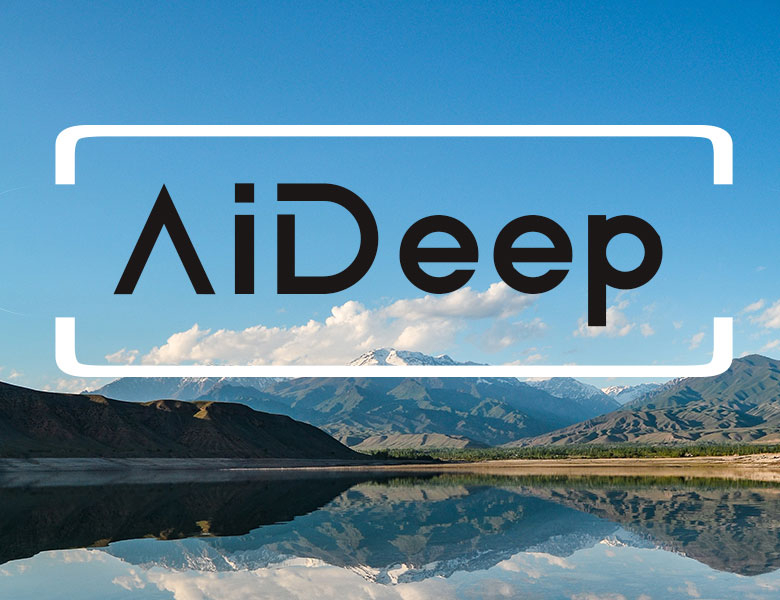
AiDeep字體是由網絡尖刀用戶體驗中心UED團隊出品的一套由公司品牌命名的免費開源字體。中文字體做了700多個,實在做不動了,所以先發了26個英文大寫+26個英文小寫,額外0-9這10個阿拉伯數字。
背景:團隊今年定位國際化,將大部分業務都定位為英文命名,所以考慮了品牌VI的標準化,為了方便,所以做了一整套字體,方便日後新業務出現還在為了各種LOGO設計而費腦筋,設計者為網絡尖刀UED團隊,小夥子。